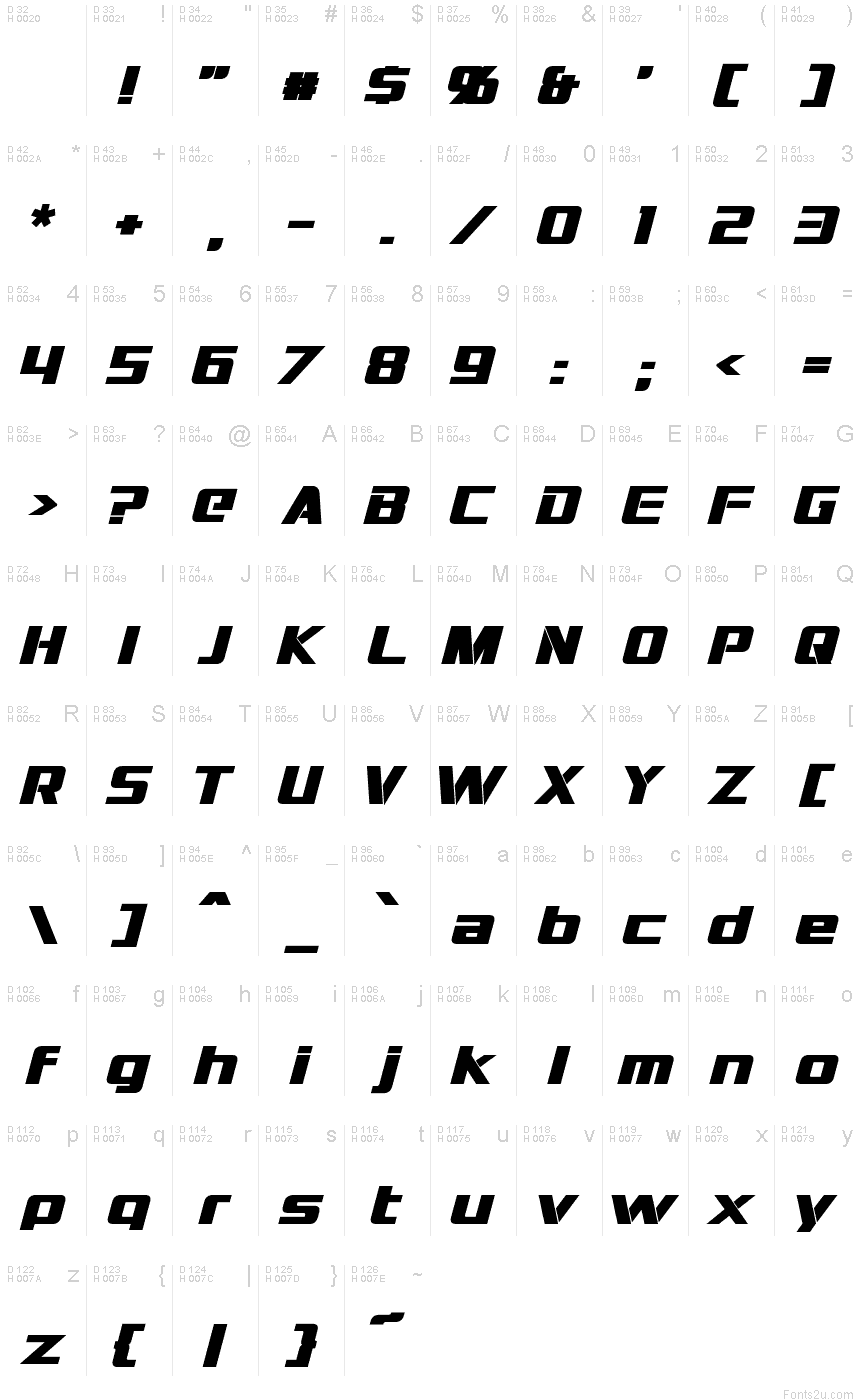
Interceptor Bold Italic von Neale Davidson ist eine kostenlose, futuristische, kursive Display-Schriftart mit einem schnellen, messerscharfen Charakter. Die Buchstaben sind stark geneigt und breit angelegt, mit wuchtigen Strichen, abgeschnittenen Ecken und langen horizontalen Schnitten, die das gesamte Design wie Motion Graphics aus einem Sci-Fi-Vorspann wirken lassen.
Sie eignet sich hervorragend für Poster, Spiele-Logos, Albumcover, Event-Flyer und Titelkarten, bei denen es auf Schnelligkeit und Wirkung ankommt statt auf Formalität. Als kostenloser Font passt sie auch perfekt zu Tech-Branding, Streaming-Thumbnails und Cover-Headlines – ideal, wenn der Text durch einen geneigten, messerartigen Rhythmus dominiert werden soll.